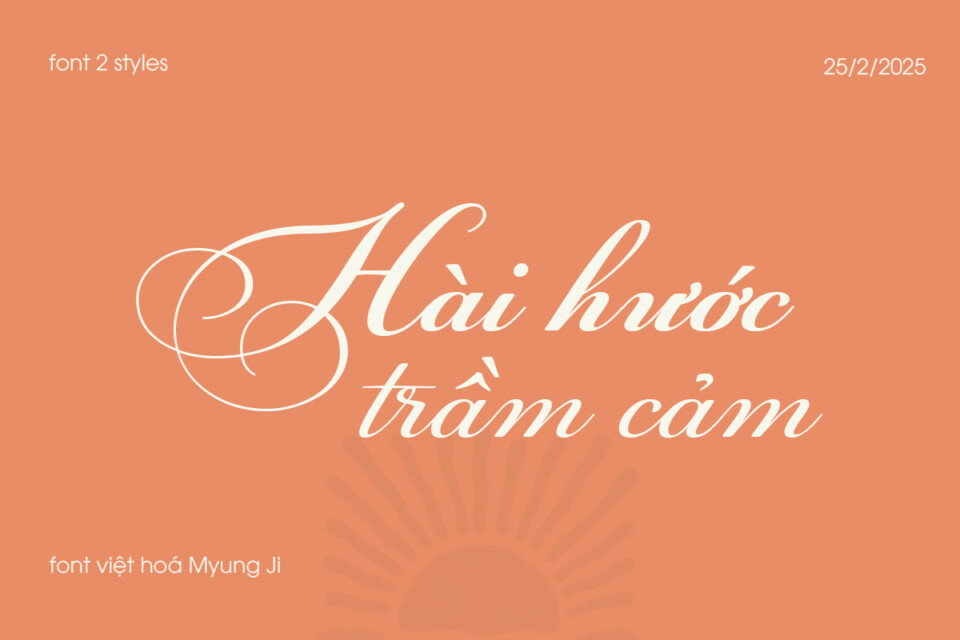
Font việt hoá MJ PFChampionScriptPro – Sự Lựa Chọn Hoàn Hảo Cho Thiết Kế Sang Trọng
Chào mừng các bạn đến với thế giới sáng tạo nơi những con chữ không chỉ để đọc mà còn để cảm nhận. Trong cộng đồng thiết kế đồ họa tại Việt Nam, nhu cầu tìm kiếm một bộ Font Chữ đáp ứng được tính thẩm mỹ cao và sự mềm mại luôn là ưu tiên hàng đầu. Font việt hoá MJ PFChampionScriptPro chính là một tuyệt tác nghệ thuật trong dòng Script, mang đến vẻ đẹp cổ điển, quý tộc và vô cùng tinh tế cho mọi dự án của bạn.
Tìm hiểu về bộ Font việt hoá MJ PFChampionScriptPro
Đặc điểm nổi bật của font chữ
Bộ Font việt hoá MJ PFChampionScriptPro nổi tiếng với những đường nét uốn lượn phức tạp và hệ thống ký tự thay thế đa dạng. Đây là font chữ được mô phỏng theo lối viết tay điêu luyện của các nghệ nhân thư pháp phương Tây thế kỷ trước. Khi được Việt hóa hoàn chỉnh, các dấu thanh đã được tinh chỉnh tỉ mỉ để không làm mất đi cấu trúc thanh mảnh nguyên bản, giúp văn bản tiếng Việt trở nên hài hòa và đẳng cấp hơn bao giờ hết.
Ứng dụng thực tế trong thiết kế
Với phong cách quý phái, bộ font này cực kỳ phù hợp cho các mẫu thiết thiệp cưới, bằng khen, bìa sách nghệ thuật hoặc các ấn phẩm truyền thông cao cấp. Trong môi trường giáo dục, giáo viên và học sinh có thể sử dụng font này để thiết kế các chứng chỉ khen thưởng hoặc trang trí slide bài giảng thêm phần sinh động. Sự kết hợp giữa nét chữ mềm mại và độ đậm nhạt uyển chuyển giúp thu hút ánh nhìn ngay từ giây phút đầu tiên.
Hướng dẫn sử dụng và kết luận